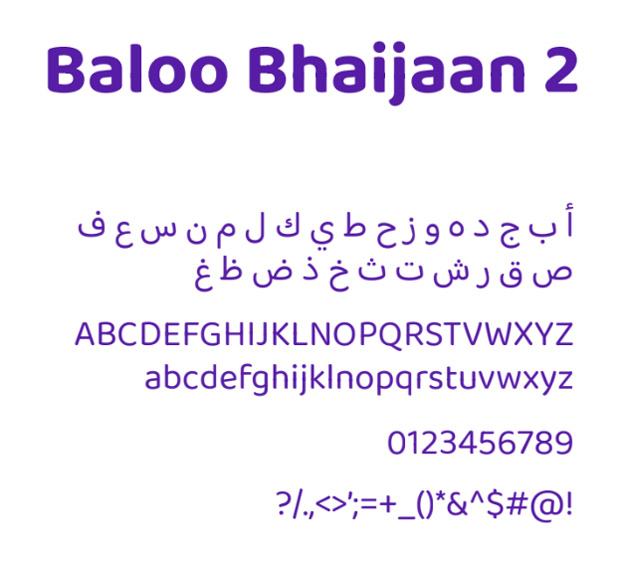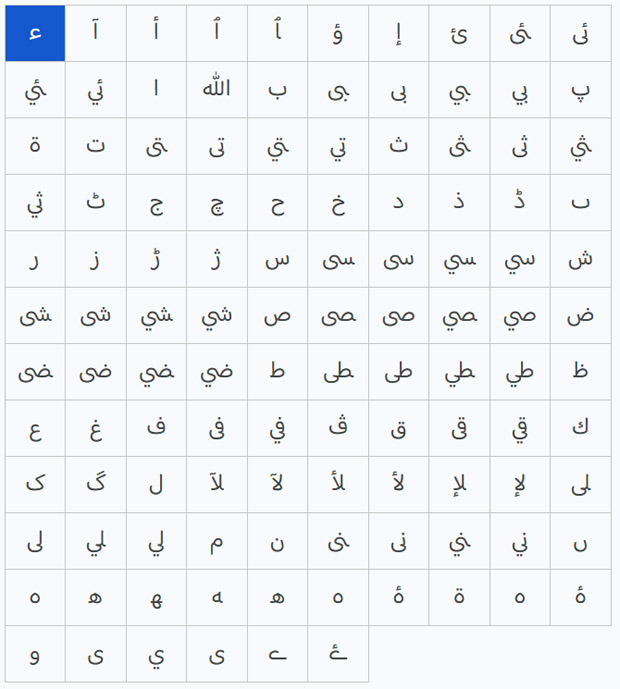
خط بالو (2) Baloo Bhaijaan المعتمد لعناوين ونصوص علامة العودة للدراسة من وزارة التعليم .. خط علامتنا العودة للدراسة هو 2 Bhaijaan Baloo، والذي تتميز حروفه بالوضوح والحداثة وسهولة القراءة، مما يعكس شخصية علامتنا. تستخدم هذه المجموعة المتنوعة من الخطوط في جميع المنتجات الإتصالية للعلامة لتوفير هوية متسقة وموحدة للكتابة. وهي متاحة للتحميل المجاني الان.
التعريف: خط بالو الرئيسي، عبارة عن مزيج مثالي بين أناقة الخطوط وجمالها، هو خط عرض ودود من تصميم إيك تايب. متوفر بتسعة خطوط هندية بالإضافة إلى العربية ونظير لاتيني، وهو متوافق مع معيار يونيكود ومرخص بترخيص حر.
بالو 2 هو امتداد لمشروع بالو السابق. يتضمن بالو 2 الجديد رموزاً إضافية، وتحسينات هندسية، وخمسة أوزان، تتراوح من العادي الخفيف إلى العريض جداً. تحافظ الأوزان الأخف على حيوية بالو المميزة، ولكن بشكل طفيف، مما يضفي حيوية على كل كلمة. هذا يسمح للخط الجديد بالتناغم بسلاسة مع النصوص بجميع أحجامها وأنماطها – سواء كانت نصوصاً قصيرة أو طويلة، عناوين رئيسية بارزة أو سطوراً قصيرة. يتميز بالو الجديد بروح مرحة وثقة عالية، وحيوية وتنوع، ويعد بإضفاء لمسة دافئة على كل مشروع.
يتألف مشروع Baloo Bhaijaan 2 من عشر عائلات خطوط تحمل أسماء محلية فريدة لكل من الأبجديات الهندية التسع بالإضافة إلى الأبجدية العربية (Baloo Bhaijaan 2). تدعم كل عائلة أبجدية هندية/عربية واحدة بالإضافة إلى اللاتينية واللاتينية الموسعة والفيتنامية.
ملاحظة: خط بالو (2) Baloo Bhaijaan متعدد اللغات (العربية، الهندية، اللاتينية.. إلخ)